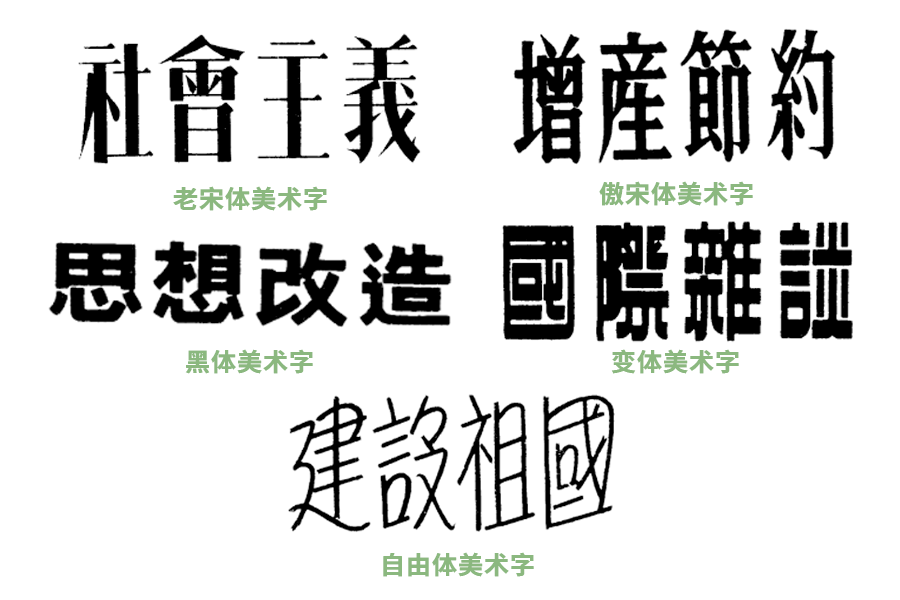
文字本质上是一种传达思想情感的手段,而美术字则是在此基础上,对其形态进行艺术化的美化处理,使之变得更加鲜活、有力,从而更有效地彰显原有文字所蕴含的意义。
美术字以基础文字为根基,经由艺术的精心雕琢,不仅保留了原文字所要传达的思想情感,还额外赋予了视觉上的美感享受,更大地提升了文字的表达效果。
平面美术字
是美术字中最基本的一种,主要用于平面设计中,如海报、广告、标志等。它的特点是在二维平面上创造出具有艺术感和装饰性的文字效果。平面美术字的设计可以根据不同的需求和创意进行变形、组合、装饰等处理,以达到独特的视觉效果。
平面美术字又可分为若干小类,如老宋体美术字、傲宋体美术字、黑体美术字、变体美术字和自由体美术字等。